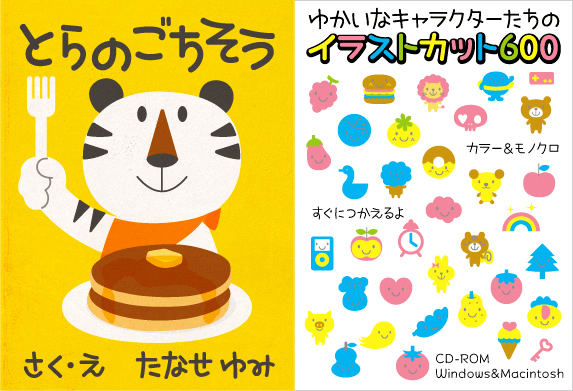
手書き風日本語フォント
Ayumu(あゆむ)フォントとは
あゆむフォントは子供が書いた手書き文字を参考にして作成した書体です。こどもらしい「たどたどしさ」「ぎごちなさ」「かわいらしさ」を文字のデザインに取り入れています。ひらがな、カタカナ、アルファベット、記号のみの書体ですが、一般的な丸ゴシックの漢字と組み合わせて使える、最適な線の太さ、デザインになっています。
例えば、こどもの教育関係での用途はもちろん、幼さの表現などに威力を発揮するフォント。
ただの丸ゴシック体では真面目すぎる、アクセントになる文字が欲しい時など用途は様々。太いボールドは見出しやタイトルにもピッタリです。手書きフォントよりも視認性が高く読みやすい、あゆむフォントをぜひお試し下さい。この下に使用例サンプルを作ってみました。          |
Ayumu(あゆむ)フォントを使った作例見本